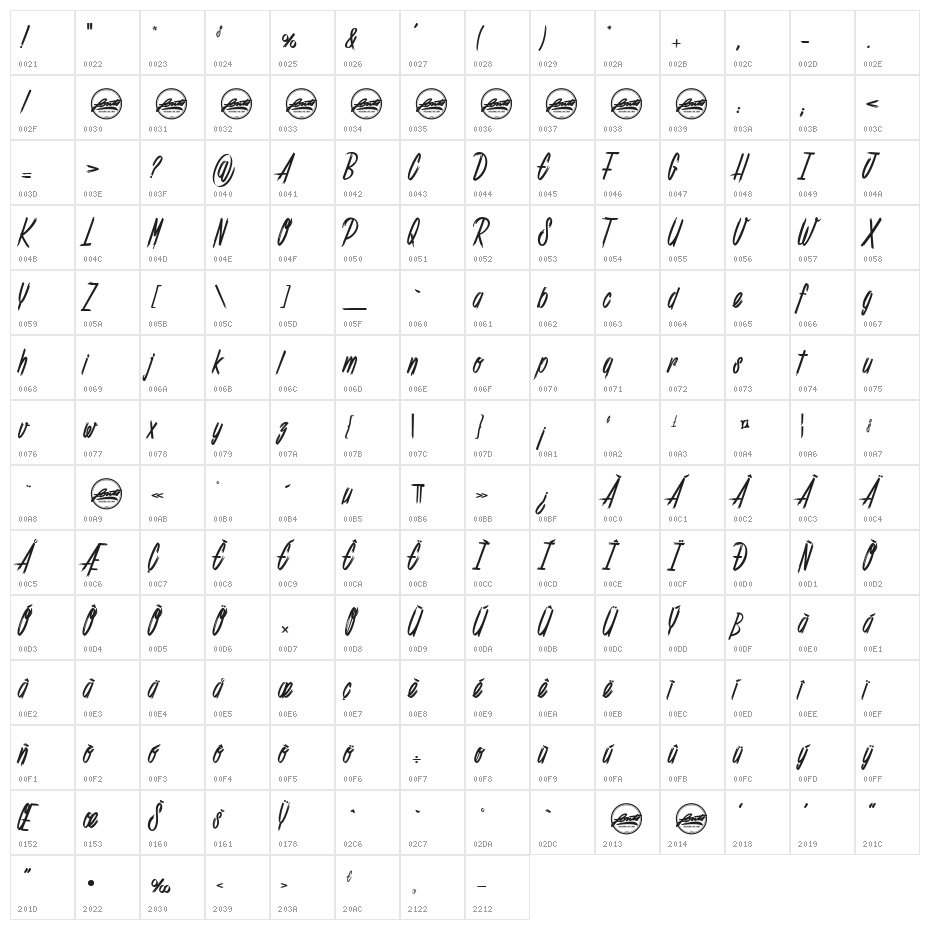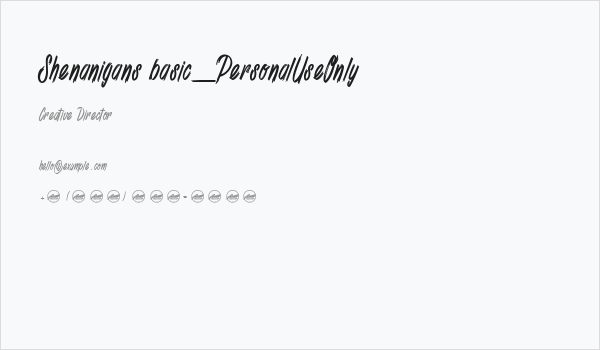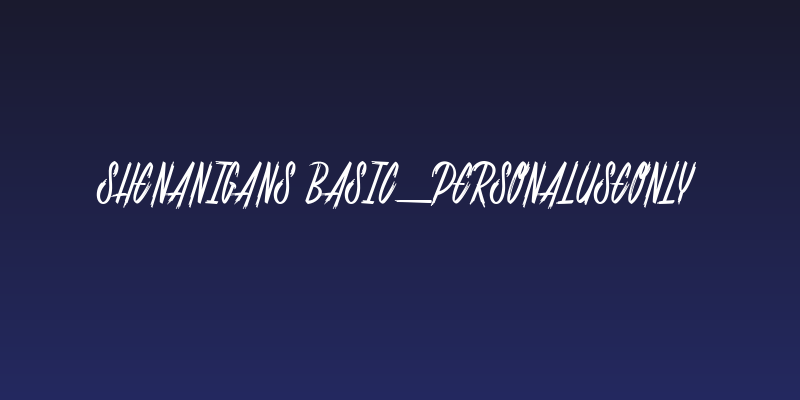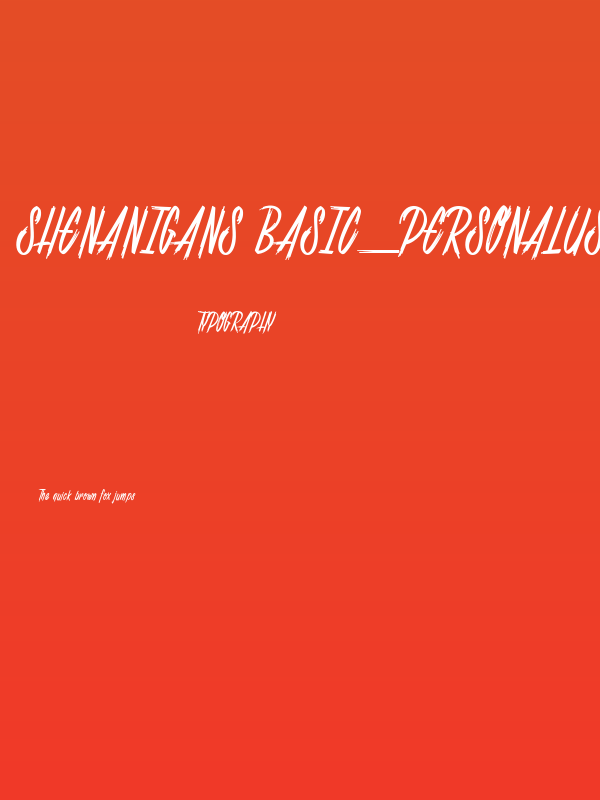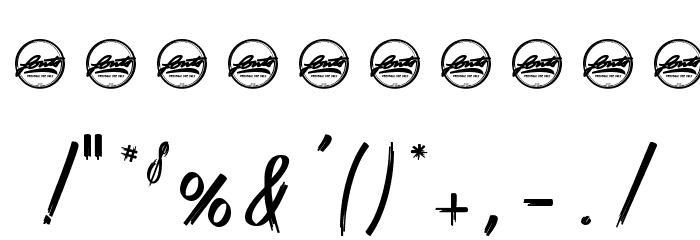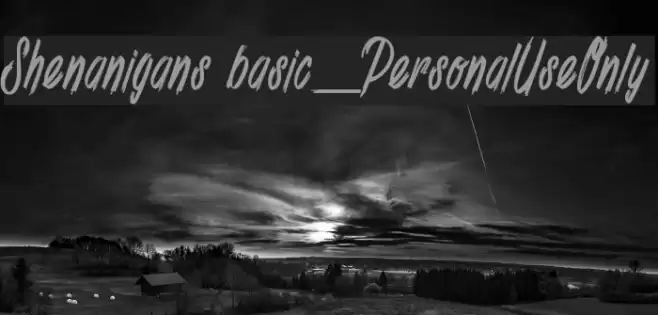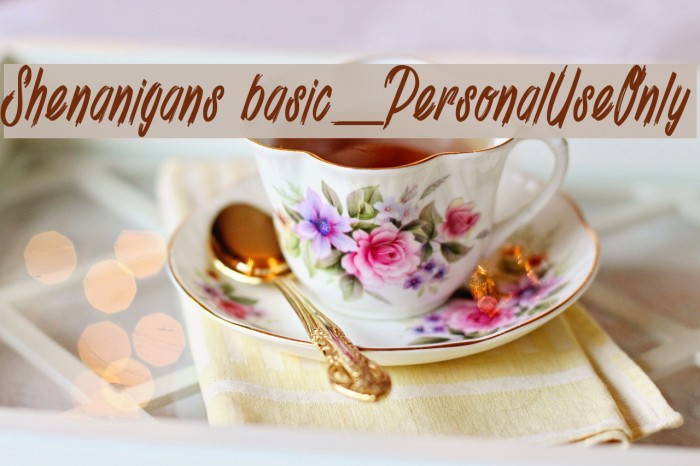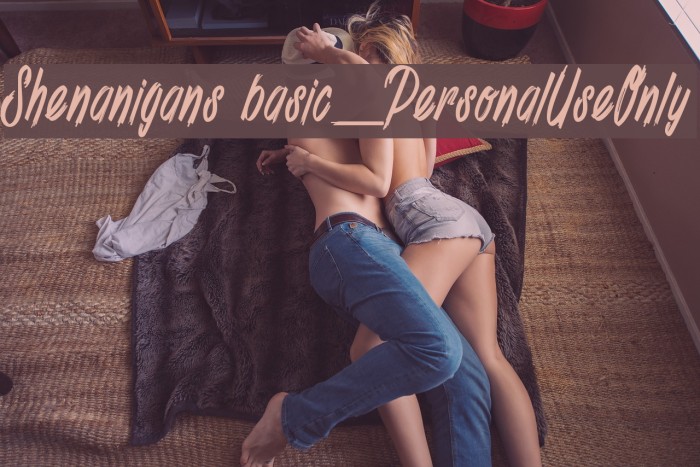
Shenanigans basic_PersonalUseOnly Font
| Рекомендуемые проекты | Ideal for posters, event flyers, social media graphics, and branding projects that need a lively and informal touch. |